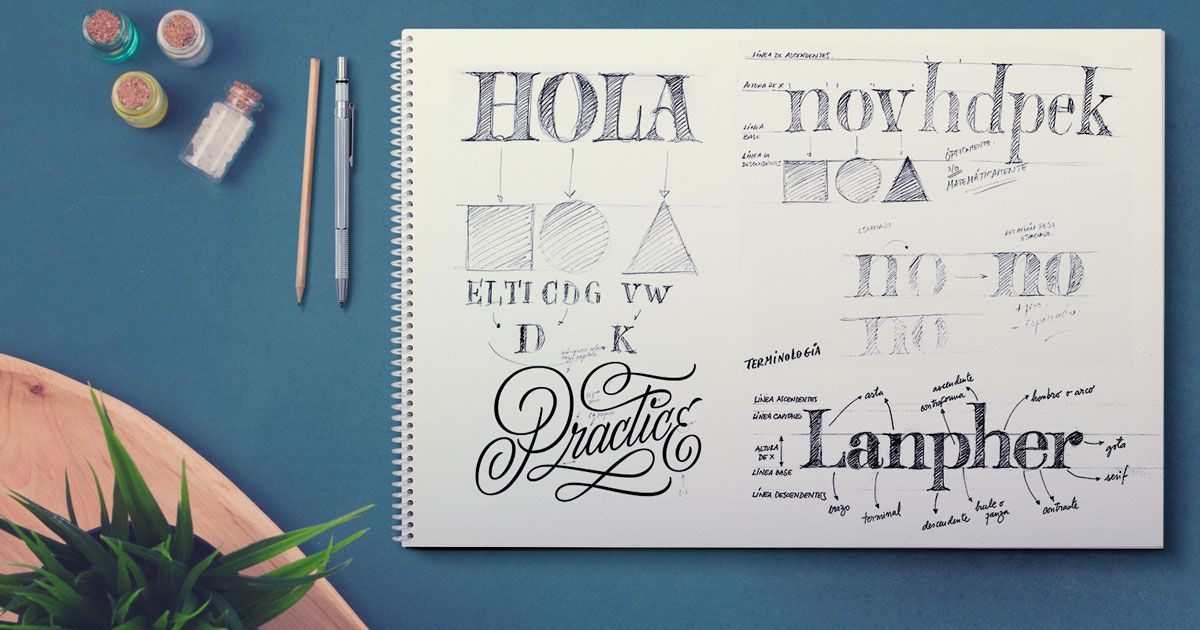
Lettering, caligrafía y tipografía, ¿conoces las diferencias?
Los tres conceptos hacen referencia a disciplinas que tienen que ver con las letras, pero se podría decir que esos son todos sus puntos en común.
La técnica de creación de las letras es completamente diferente y no es extraño que surjan dudas entre quienes no están plenamente familiarizados con el tema. Hacemos un breve repaso de qué es el lettering, la caligrafía y la tipografía y cuáles son las diferencias entre ellas, describimos las características de cada disciplina y mostramos ejemplos con el fin de contribuir a la correcta designación de cada una de las materias y tratar de evitar la confusión ente unas y otras que con tanta frecuencia se da tanto en diseñadores noveles como en ámbitos más experimentados.
Caligrafía
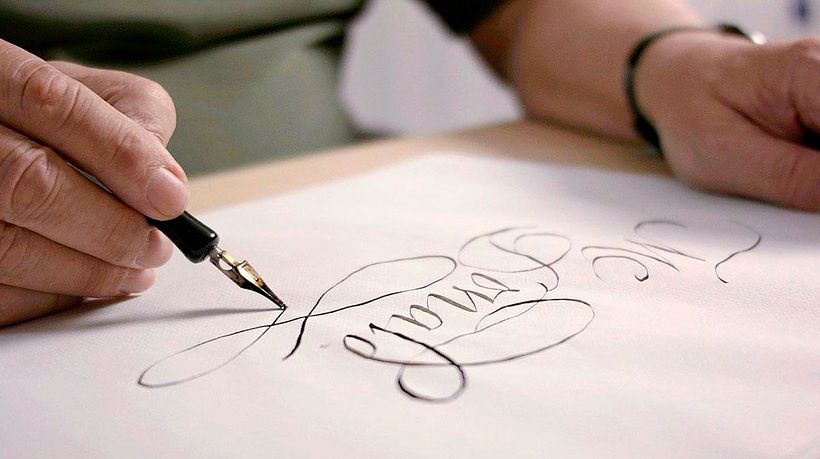
Esta disciplina consiste en dibujar o escribir letras prestando atención al modo, la dirección, la secuencia y la velocidad a la que se dibujan los trazos o rasgos que las componen. La caligrafía necesariamente debe realizarse a mano, generalmente con plumas, rotuladores, pinceles..., aunque pueden utilizarse medios digitales (como una tableta) siempre que la letra sea manuscrita.Cada parte significativa de una letra debe estar delineada con un solo trazo y no admiten correcciones, de esta manera cada una de las letras es única y el autor de una caligrafía es la persona que la dibuja.
Lettering
A diferencia de la caligrafía, el lettering consiste en dibujar letras o palabras, no en escribirlas; esto implica que los trazos pueden ser corregidos. Otra diferencia con la caligrafía es que las letras pueden generarse analógicamente o a partir de vectores y otros métodos digitales, lo que implica que no necesariamente cada letra será única, sino que estas pueden copiarse dando al conjunto un aspecto más uniforme. Sin embargo, el autor del lettering, a diferencia de lo que ocurre con la tipografía, donde no es así necesariamente, es quien ha dibujado las letras.
Tipografía
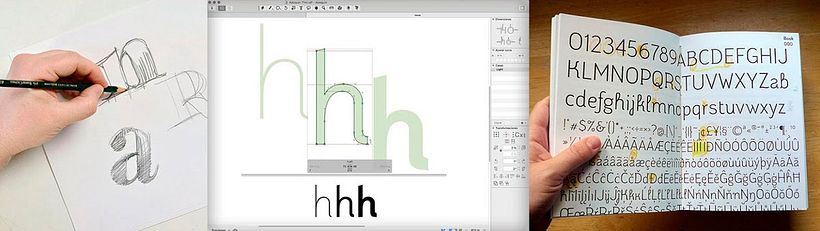
Los diseñadores de tipografías no crean letras o glifos únicos e irrepetibles como los calígrafos, ni dibujan palabras como los letristas; una tipografía es un conjunto único de caracteres que comparten una unidad estilística. Esto quiere decir que el diseñador de tipografías no sólo diseña las letras, sino que también las programa y establece una serie de parámetros esenciales que se repiten sistemáticamente en ese conjunto de caracteres.
Todo esto, aunque pueda parecer sencillo en a la hora de aprenderse la teoría, se transforma en verdaderos quebraderos de cabeza para quienes no son capaces de discernir entre un concepto y otro con facilidad o no tienen claras las diferencias entre una lettering, caligrafía y tipografía, dando lugar a grandes confusiones.